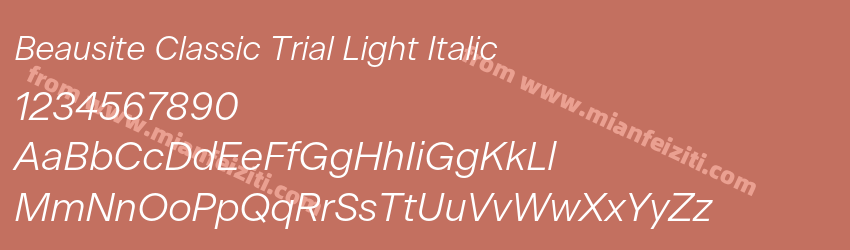
Beausite Classic Trial Light Italic
字体名称: Beausite Classic Trial Light Italic
Postscript名称: BeausiteClassicTrial-LightItalic
本款“Beausite Classic Trial Light Italic”是一款书写很新颖的字体,字体大方,适合各种设计作品使用!欢迎下载!